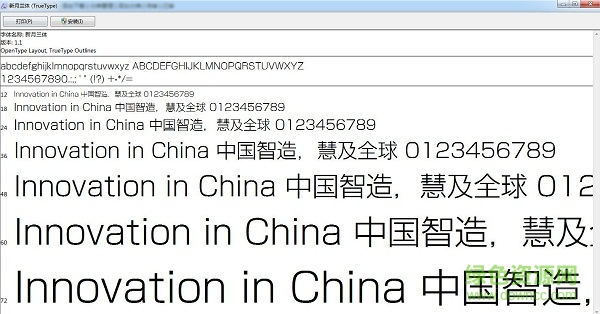
軟件介紹 軟件標(biāo)簽: 新月蘭字體 日文字體 新月蘭字體是一款日本無襯線字體,包含了粗體和亮體兩款,內(nèi)部空間大小適中,比例合當(dāng),適用于屏幕顯示、平面設(shè)計等各個領(lǐng)域,有需要著歡迎免費下載!新月蘭體特點一款筆畫較細的日系舊字形字體,新月蘭是以日文Shingo的舊字形漢字,以蘭亭纖黑補全的一個合并字體。英文數(shù)字可以搭配Lato Light使用。日文字體推薦a otf 日文字體 授權(quán):免費軟件 WinAll, WinXP, Win7大小:5.9M語言:中文aotf日文字體是一款常用的日系字體,這款字體筆畫干凈,筆鋒銳利,結(jié)構(gòu)平穩(wěn),整體充滿美感,形似中文隸書字體,需要這款字體的小伙伴快來綠色資源網(wǎng)下載吧1aotf字體安裝說明方法一:請先用winrar等壓縮軟件解壓,然后下載地址新月蘭體使用說明將字體文件復(fù)制到C:\Windows\Fonts文件夾即可完成安裝(Win7用戶可直接右鍵選擇安裝菜單進行安裝) 軟件截圖 上一張下一張(1 / 1) 安裝詳細截圖 猜你喜歡 日文字體 日文字體 日文字體是一類日系風(fēng)格的書法字體,日本文化起源于中華唐朝,延續(xù)了華夏文明的底蘊,同時也加入自己的本國特色,綠色資源網(wǎng)提供日本字體大全,歡迎大家下載使用! 查看更多>> hgp明朝e 320KB/中文/1.2/下載 hgp明朝b 350KB/中文/2.2/下載 ksw般若お試し教育漢字 2.44M/中文/5.0/下載 FGPイワタ細教科書體 2.98M/中文/5.0/下載 游教科書體字體 4.11M/中文/7.5/下載 紫羅蘭永恒花園京紫文字體 21KB/中文/5.0/ttf下載 其他版本下載 標(biāo)題 大小 更新日期 下載 下載地址 電腦版 新月蘭體 粗體/亮體 點擊報錯 軟件無法下載或下載后無法使用,請點擊報錯,謝謝! 關(guān)閉報錯反饋 請描述您所遇到的錯誤,我們將盡快予以修正,謝謝! *必填項,請輸入內(nèi)容 本類最新 首爾南山體字體 v1.06 官方版 潮字社風(fēng)云簡ttf 潮字社凌渡鯤鵬簡體字體 潮字社曾玉波手書簡字體 微博慧心字體 阿里巴巴iconfont字體庫 用戶評論 熱門評論 最新評論 發(fā)表評論 查看所有評論(0) 昵稱: 請不要評論無意義或臟話,我們所有評論會有人工審核. 字數(shù): 0/500 (您的評論需要經(jīng)過審核才能顯示)